パンダがフォント化、本当か、謎のパンダ体
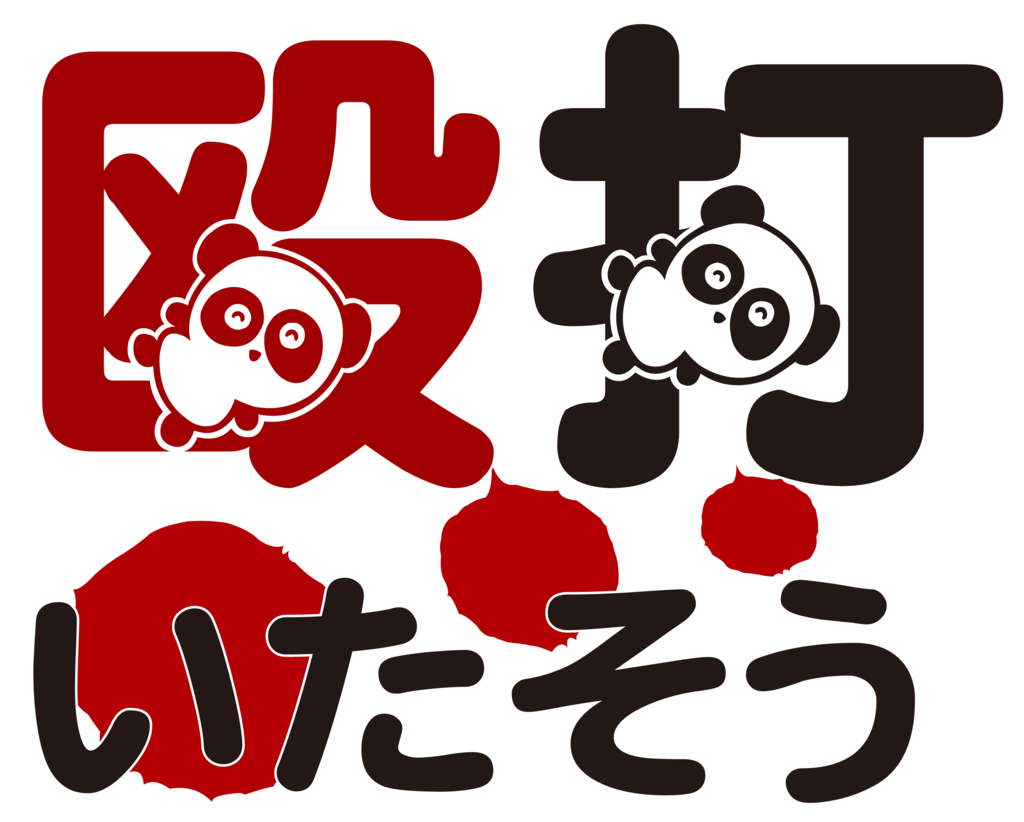
よく見たら、煽ってそうなパンダの表情になんかじわじわイラっとくる。
パンダ体
丸ゴシック系フォントでありながら、漢字部分にパンダのイラストがくっつているという何処でどんな場面で使用するのか謎だったフォント。シャンシャンブームが訪れそうな現在、そのフォントを使用する最大のチャンスだと思われる。